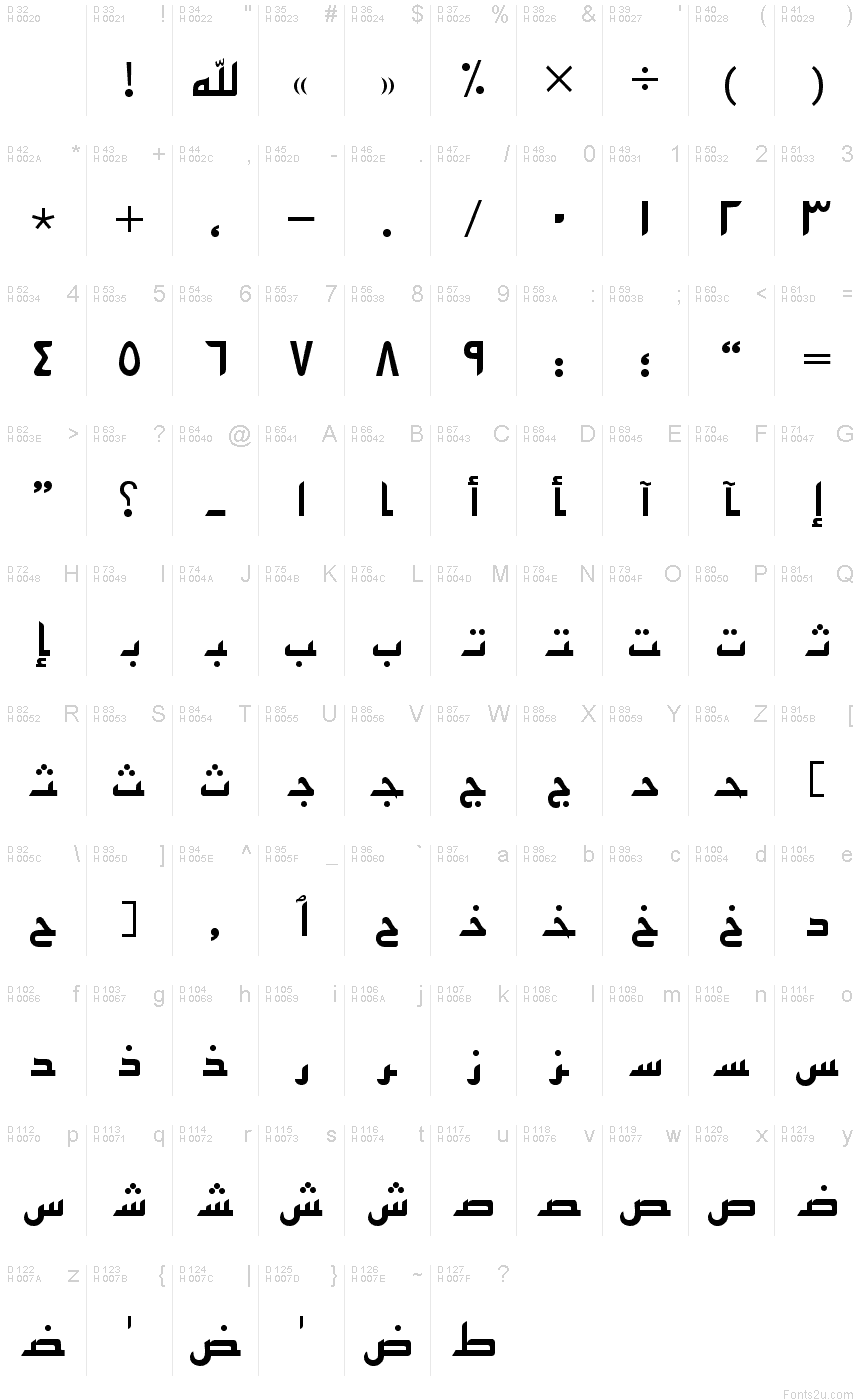
ArabicKufiSSK
Arabic Kufi SSK, przypisywana Southern Software, to darmowy, geometryczny, arabski krój kuficki o niskiej, poziomej sylwecie i szerokich, obłych formach. Okrągłe kropki podkreślają kanciaste połączenia i kwadratowe piony.
Potrafi przekształcić liternictwo w architektoniczny pas do projektów kulturalnych i oznakowania wystaw. Zdecydowana geometria sprawdza się również na okładkach książek i plakatach wydarzeń poświęconych sztuce lub historii arabskiej. Najlepiej sprawdza się w zastosowaniach akcydensowych (display), gdzie linia bazowa staje się obramowaniem lub ramą.